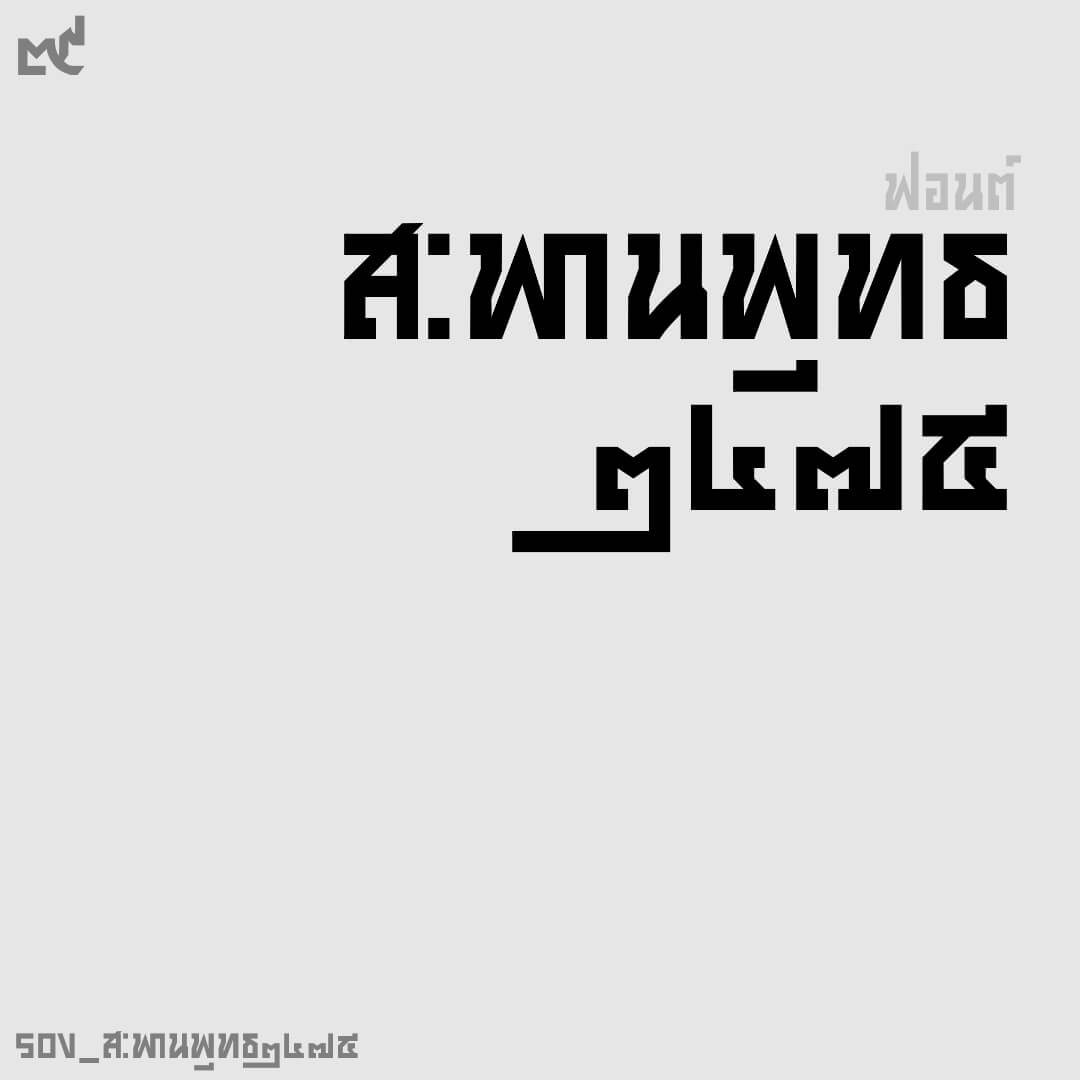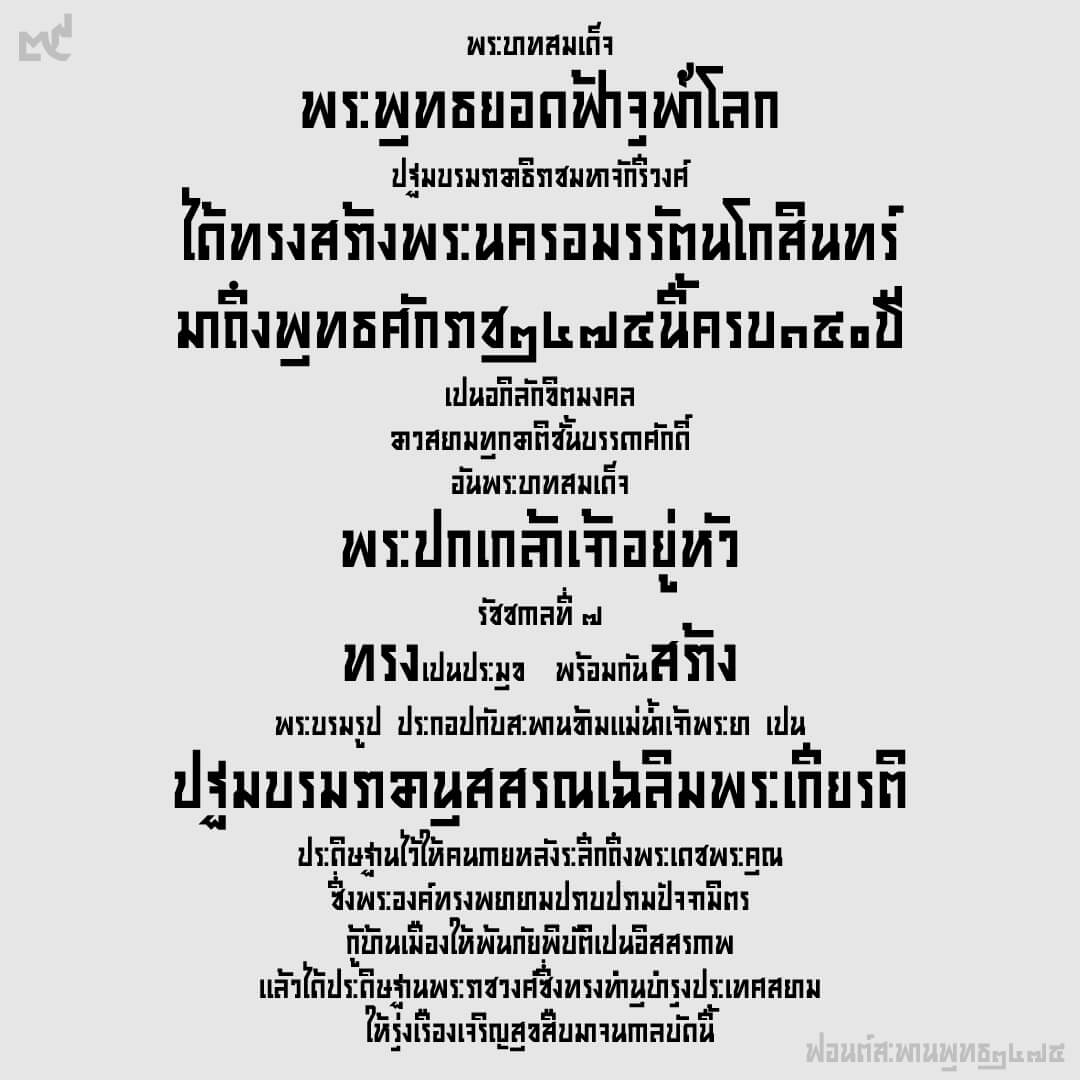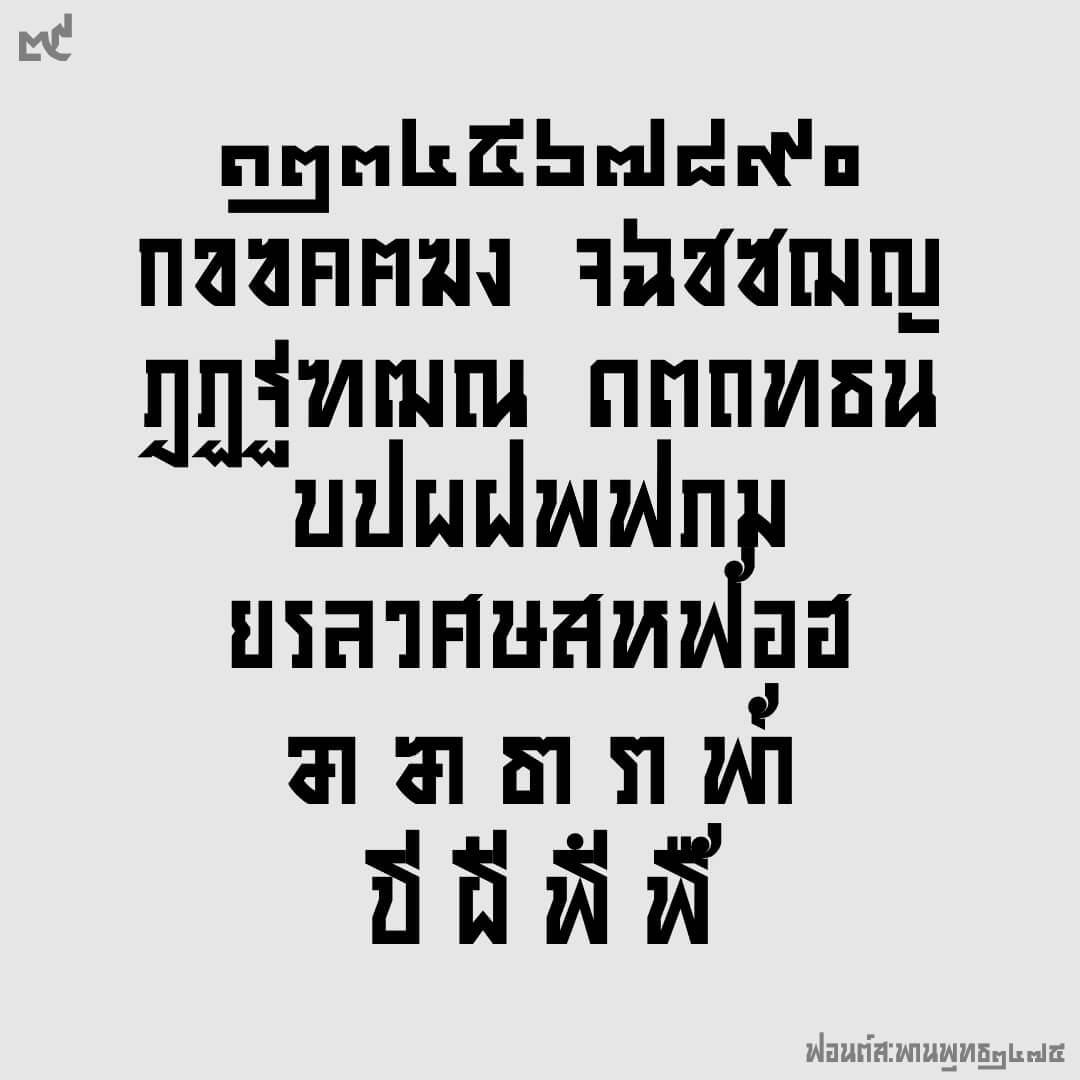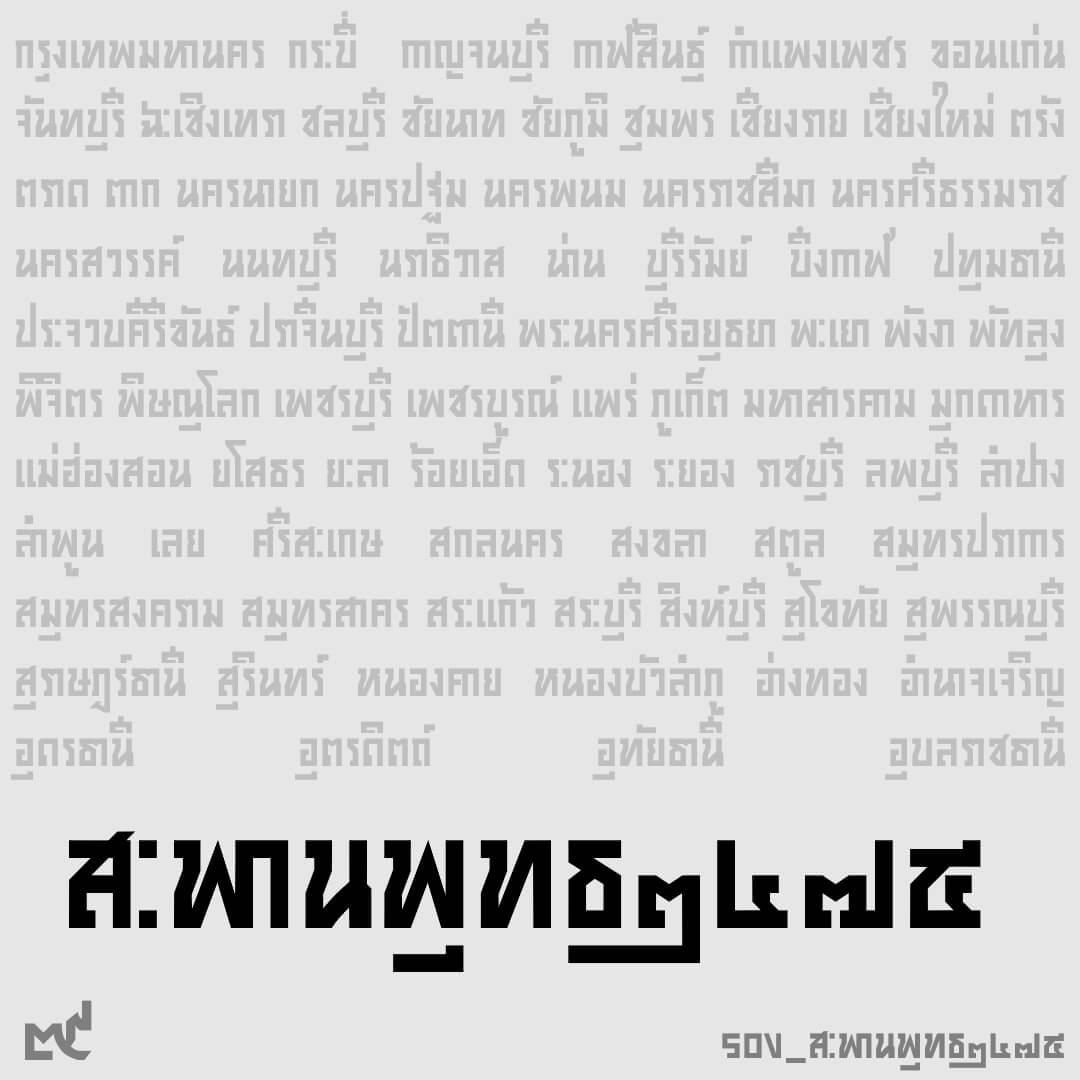
ฟอนต์สะพานพุทธ๒๔๗๕ – ต้นทางจากอักษรในจารึกพระบรมรูป ร.๑ เชิงสะพานพุทธ พ.ศ.๒๔๗๕ มีอักษรแปลกตาจากอักษรในตำราเรียนปัจจุบัน
ปล.แล้วก็ไม่ได้ทำ kerning ให้นะจ๊ะ… อย่าลืมเอาไปขยับเอง
สะพานพุทธ๒๔๗๕ (SOV_spanputh2475)